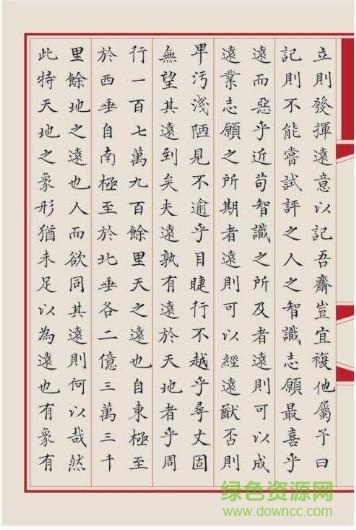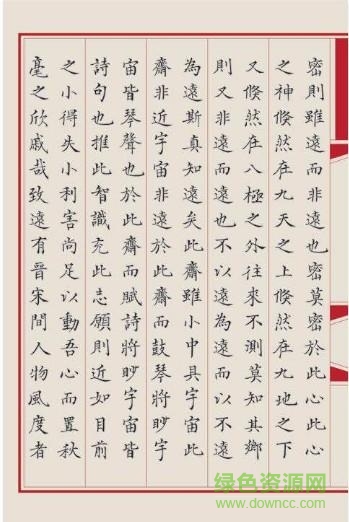
漢儀新蒂永樂大典體是根據(jù)我國著名文獻永樂大典定制而出的字體,獨居特色的筆鋒讓字體看起來更加的蒼勁有力,全新的字體讓文章排版看起來更加的新穎舒適,需要的用戶快來綠色資源網(wǎng)下載吧!
漢儀新蒂永樂大典體,《永樂大典》是我國文學界非常重要的一部文獻,由于戰(zhàn)亂,所剩無幾,為了紀念這部文獻,漢儀字庫設計出了這款新蒂永樂大典字體,根據(jù)臨摹的副本的2000多字,又擴展了9000多字,一共是不到12000字,可以說已經相當不錯了。
1、拉丁字符部分的設計,采用了與明朝永樂年間同時期14世紀西方抄經字體,中英文混排中,也體現(xiàn)出了意外的協(xié)調性。
2、全面手寫臨摹了副本中的書法兩千余字,并通過認真分析,仿寫擴展了9000余字,包括簡體字,制作完成了超過11000字。